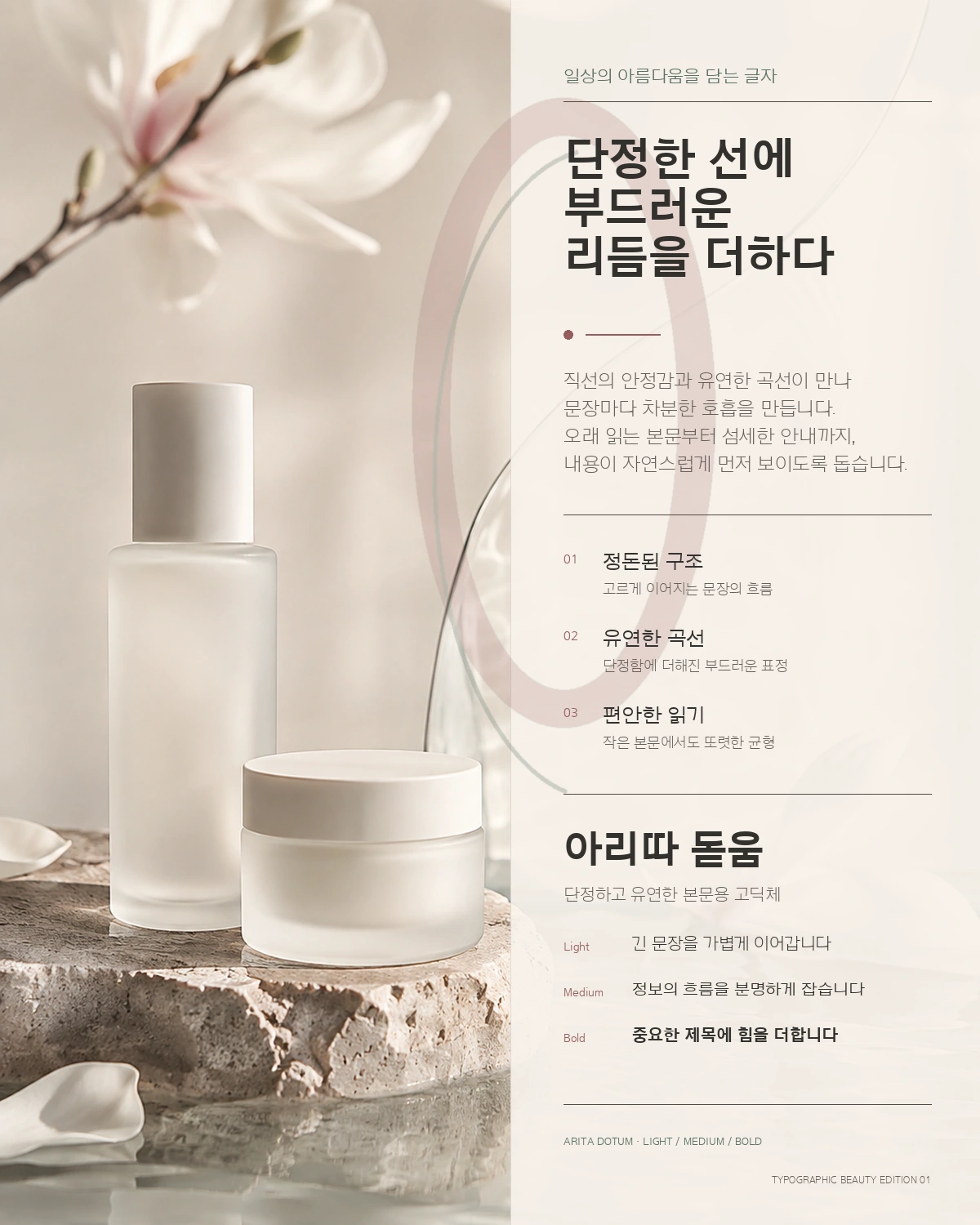
아리따돋움 — 아모레퍼시픽에서 배포하는 무료 폰트입니다. 직선적인 돋움의 틀에 부드러운 곡선을 더해 단정하면서도 유연한 표정을 만든 본문용 고딕체
아모레퍼시픽이 2005년부터 만들어 온 기업 전용 글꼴 아리따 가족의 민부리 쪽입니다. 아리따는 2004년에 시작해 16년에 걸쳐 디자이너 15인이 참여했고, 세 개 언어 18종 35,115자 규모로 완성된 장기 프로젝트입니다. 이름은 시경의 첫 시 관저에 나오는 아리따운 아가씨에서 따왔습니다.
돋움 특유의 직선적이고 딱딱한 인상을 곡선으로 눅인 것이 이 서체의 방향입니다. 글자의 기본 뼈대는 안정적으로 두되 획과 자소가 만나는 곳에 유연한 곡선을 넣어, 고딕의 명확함과 부드러운 표정을 함께 담았습니다. 파일을 재어 보면 받침이 있든 없든 글자 높이가 거의 변하지 않는 네모틀 구조이고, 가로세로 획의 굵기 차이도 크지 않습니다.
Thin부터 Bold까지 다섯 굵기가 있어 본문과 제목의 무게를 세밀하게 조절할 수 있습니다. 다만 쓰기 전에 라이선스를 반드시 확인해야 하는 서체입니다. 판매용 제품과 포장 상자에는 쓸 수 없고 CI나 BI로도 쓸 수 없으며, 인쇄물에 쓸 때는 이 제작물은 아모레퍼시픽의 아리따글꼴을 사용하여 디자인 되었습니다라는 문구를 6px 이상 크기로 넣어야 합니다.